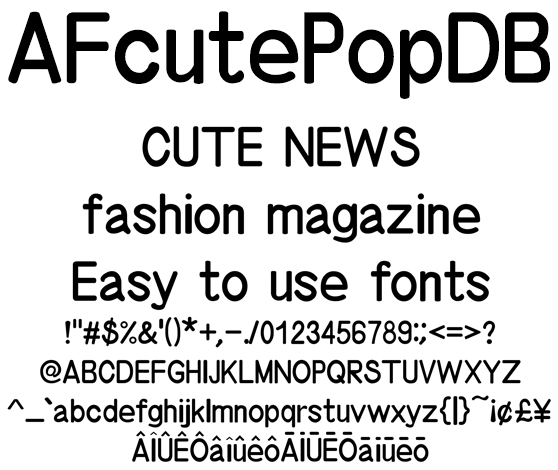
キュートな丸ゴシック欧文フォント AFcutePopDB
AFcutePopDB
とにかく目立つ丸ゴシックなデミボールド欧文フォントは、キャッチな場面の同人系、コミック、アニメ、ゲームに最適。パンフレット、リーフレット、フライヤー、ファッション系コンテンツに使えるフォントです。日本のローマ字表記で使われる訓令式やヘボン式で扱う Ô や Ō を収録、人名地名へのアプローチもリアルです。